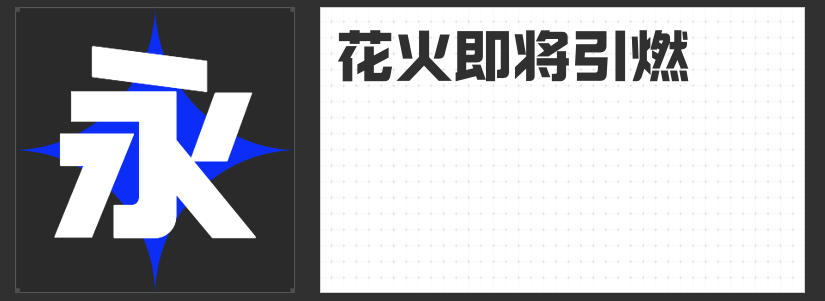
奥运会平面设计字体推荐:激扬文字,共绘奥运辉煌
随着2024年巴黎奥运会的开幕。在这场创意与激情的碰撞中,字体的选择尤为关键,它不仅承载着信息传递的功能,更是文化与艺术的展现窗口。今日,我们特别推荐四款字体,它们各具特色,完美契合巴黎奥运会的精神内核。
励字勇敢黑简 特黑:这款字体以其独特的硬朗线条和强烈的视觉冲击力,象征着运动员们不屈不挠、勇往直前的精神风貌。特黑的加粗处理,让每一个字都仿佛蕴含着无限的力量与决心,非常适合用于标题或封面设计,瞬间点燃观众的热情与期待。
造字侠灵霄简繁 传神:这款字体融合了硬笔书法与现代设计的美感,既保留了传统文化的韵味,又不失现代设计的简洁明快。传神之处,在于其笔画的流畅与结构的和谐,为巴黎奥运会增添一抹东方文化的神秘与优雅。
励字暴风简 超级黑:暴风之名,预示着速度与激情的碰撞。超级黑字重的极致对比,让字体在任何背景下都能脱颖而出,如同赛场上风驰电掣的运动员,展现着速度与力量的完美结合。这款字体适用于动态海报或赛事直播的标题,让人一眼难忘,感受奥运的激情与活力。
高手兵克行江湖:这款字体带着一种江湖侠士的豪迈与不羁,每一笔一划都透露出力量与智慧。它不仅仅是一种文字表现形式,更是一种精神的传递,与奥运会上各国健儿以技会友、追求卓越的精神不谋而合。在赛事介绍或文化宣传中运用此字体,能够营造出一种跨越国界、共同逐梦的宏大叙事。
综上所述,这四款字体各具特色,无论是从视觉冲击力、文化内涵还是情感共鸣上,都能为奥运会相关的平面设计增添无限可能。让我们携手这些激扬的文字,共同绘制奥运的辉煌篇章!